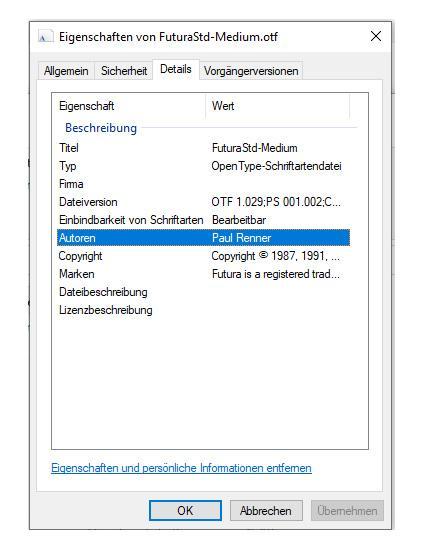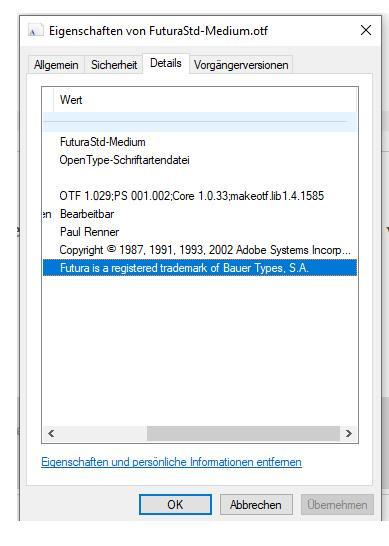
Futura Std im Detail - Lizenzierung der exakt identischer Font-Schnitte
vor ungefähr zwölf Jahren habe ich mehrere Schnitte der  Futura Std käuflich erworben. Exakt diese Schnitte möchte ich jetzt für eine andere Firma lizenzieren. Bei der Suche nach Futura Std ist bei den Anbietern meines Vertrauens nur noch die Futura Pro zu finden. Die Futura PT innerhalb der Adobe CC hat ein völlig anderes Schriftbild und fällt daher aus.  Könnt ihr mir beantworten, ob das Schriftbild der Futura Pro tatsächlich dem der Futura Std von damals entspricht? Wenn ich also den Font eines Textes von Std durch Pro ersetze, sollte sich nichts ändern - es geht mir ausschließlich darum, dass die alten Dokumente mit dem neuen Font genauso aussehen wie davor.
Std und Pro sind Bezeichnungen von Zeichenbelegungen. Kann also gut sein, dass die zugehörige Pro-Version bis auf die Zeichenbelegung ansonsten identisch ist. Das müsste man beim Hersteller erfragen. Welcher das ist, hast du noch nicht verraten. Hängt aber auch mit der Versionsnummer zusammen. Sofern Name und Versionsnummer nicht identisch sind, würde ich nie davon ausgehen, dass sich absolut nichts im Textfluss oder Design ändert.
leider kann ich überhaupt nicht mehr rekonstruieren, wo damals lizenziert wurde. Der Verantwortliche dafür ist 2019 nach Unbekannt verzogen. Die Zeichenbelegung ist nicht das Problem, eher die Laufweite und Mittelhöhe. Vermutlich kann ich meine Fonts nicht zu - meinetwegen - myfonts schicken und fragen ob die Futura Pro identisch aussieht? Jedenfalls wenn ich direkt bei myfonts oder Linotype nach Futura Std suche, komme ich direkt zur Futura Pro.
Das würde mich sehr wundern, dass da andere die Verantwortung für die Entscheidung übernehmen, bzw. würde ich mich auch nicht darauf verlassen wollen.
Mit Glück und Verhandlungsgeschick könnte ich mir, wenn überhaupt, den umgekehrten Weg vorstellen: Man schickt dir vorab die aktuellen Fonts zum Testen, und du entscheidest dann, ob sie für dich taugen oder nicht.
Der Anbieter der Futura Std sollte sich aus den Font-Daten auslesen lassen. Den würde ich dann kontaktieren und das Problem schildern. Das sollte sich eigentlich lösen lassen ...
Jedenfalls langer Rede, kurzer Sinn: Gute Foundrys packen alle relevanten Informationen in eine Font-Datei. Das Fehlen jeglicher Information muss nicht zwingend bedeuten, dass so ein Font aus einer, äh, dunkleren Quelle stammt, es gab einen gewissen Wildwuchs zu den Zeiten von Formatwechseln, whatever zu Truetype, ps1 zu Truetype und dann irgendwann alles zu Opentype.
nein, bitte, alles gut.  Aber was sollen mir jetzt die weiteren Infos sagen? Da steht doch nichts Verbindliches?
also wer ist Bauer Types, S.A.? nie davon gehört. 😕
also wer ist Bauer Types, S.A.?
Das ist nicht relevant. Das Copyright liegt laut deinem Screenshot bei Adobe.
Bauer Types dürfte ein Rechtsnachfolger der Bauerschen Gießerei sein bei der die Futura ursprünglich als Bleisatzschrift erschien. Der Name »Futura« wurde dann als Marke eingetragen und ist geschützt.
Danke, ich suchte schon nach einem Javascript-Teil, aber das ist meiner Erinnerung entgangen!
Ich hab noch einen Distributor für die Adobe Futura STD gefunden, der zumindest auch beim zweiten Blick nicht illegitim aussieht: https://www.philsfonts.com/font-family/adobe/futura-complete-family-pack-adobe/MA14706399/
ok, die check ich dann auch. Also ein richtiges Budget muss ich nicht einhalten, aber bei 350,- Öcken plus steigt die Firma vermutlich aus. Zusammengefasst: Das alles wollte ich wissen. Also tyomm
Wenn euch das interessiert, schreibe ich hier gerne mein Font-Endergebnis rein. lg